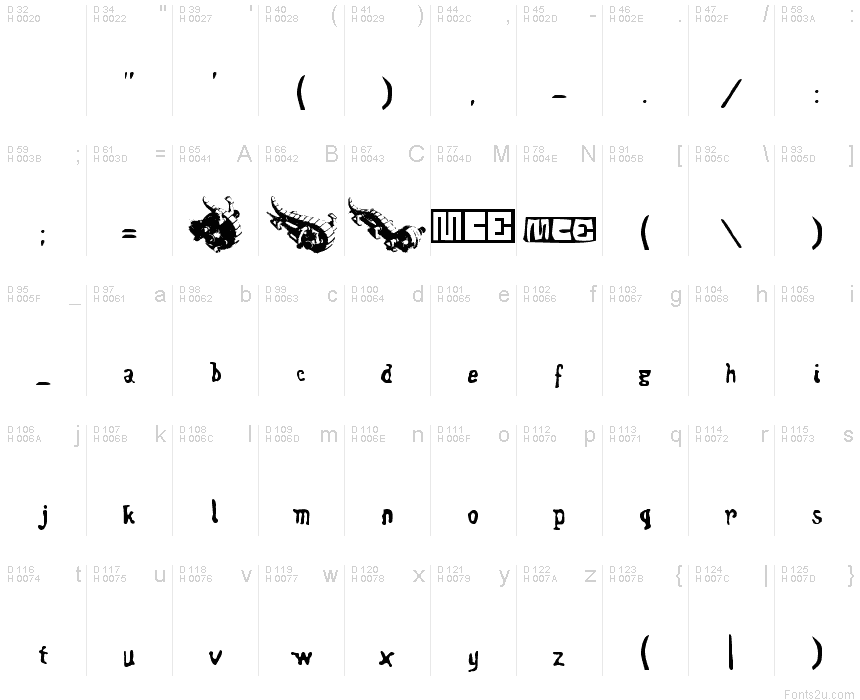
خط Wentleteefje، من تصميم Maurits Cornelis Escher & LOKI، هو خط عرضي (display) مجاني ذو طابع متآكل يضفي لمسة من الغرابة الماكرة التي تشبه قصص الحكايات. تبدو الحروف ناعمة وبالية، مع منحنيات غير منتظمة، وحواف خشنة، وخطوط عمودية ممتدة أحياناً، مما يجعل الخط يبدو كأنه نصف ذائب ونصف منحوت يدوياً.
تتناسب هذه الأجواء تماماً مع عناوين الملصقات، وأغلفة الكتب، والقصص المصورة المستقلة، وعناوين المجلات (zines)، والتغليف المبتكر، حيث يبدو القليل من عدم الانتظام أكثر إنسانية من الدقة الجامدة. وبكونه خطاً مجانياً، فهو خيار رائع أيضاً لبطاقات العناوين، والاقتباسات القصيرة، وشعارات الكلمات المختصرة، لأن صورته الظلية الخشنة تنقل شخصية الخط قبل أن تلاحظ التفاصيل حتى.